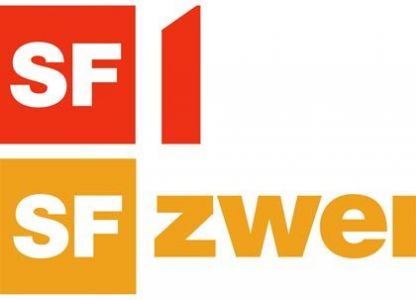
Ach die Schweizer...
Was sagt ihr zum neuen Auftritt des Schweizer Fernsehens. Ich sage: Wieder einmal eine grosse Schweizer Firma (man erinnert sich an Credit Suisse), die gescheiter bei ihren alten Logos bleiben würde!
ps. Leitung des Redesigns hatte Alex Hefter (ZDF).
Etwas besser. Denke ich. Vor allem finde ich diese Vermischung von Ziffer (SF1) und ausgeschriebenem Zahlwort (SF2) etwas eigenartig. Da ich vor einigen Jahren den Fernseher verkauft habe, kann es mir aber egal sein.
ich finde das nicht gelungen. mir mag das alles nicht so recht zusammenpassen:
und dann eben noch die zwei, die im startposting gezeigt wurden. wie soll das denn alles zusammen und nebeneinander wirken?
Beim letzten Logo habe ich mich erst gefragt, was SFIOVORIO eigentlich sein soll. Dann habe ich gedacht, es sei eine Designstudie, bei der irgendjemand komatös über der Tastatur zusammengebrochen ist, und Sekunden später erst habe ich die Zahlen erkannt. – Leserfreundlich ist anders!